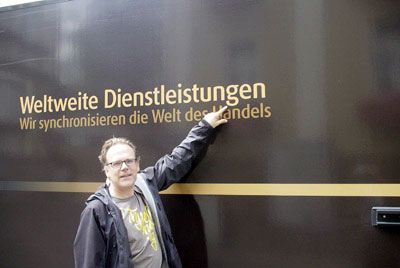
Lizenzstreit: FSI schließt VergleichAuf Typophile erschien in den frühen Morgenstunden eine
Pressmitteilung von FSI FontShop International zu einem länger
schwelenden Schriftlizenzstreit: Man habe sich mit einem nicht genannten
Corporate-Design-Unternehmen verglichen. Kommentatoren im Forum steuerten Ross
und Reiter bei: es geht um die Schrift FF Dax, von Future Brand
für das Redesign des Logistik-Konzerns UPS eingesetzt und nach
Auffassung von FSI nicht ordentlich lizenziert. Weiterlesen ...
Bei der beklagten Schrift handelt es sich um eine (so die Schriftexperten
bei Typophile) eigentümlich modifizierte FF Dax mit einem kleinen
g aus der FF Meta, ebenfalls eine Schrift aus FSIs
FontFont-Bibliothek. Dieser Zwiebelfisch war dem Fontblogger schon vor Monaten
aufgefallen:
![]() Zwiebelfisch: Der Kleinbuchstabe g passt nicht zur Grundschrift Die Übersetzung der Pressemitteilung: »FSI Fonts und Software GmbH (FontShop International) gibt heute bekannt, dass es einen Vergleich mit einem international anerkannten strategischen Markenentwicklungsunternehmen geschlossen hat, dessen Gegenstand eine Streitigkeit über Entwurf, Schöpfung und die Lizenzierung einer Schrift war – Bestandteil einer Arbeit für einen Kunden dieses Unternehmens. Das Unternehmen bestritt und verteidigte sich energisch gegen Vorwürfe, dass die besagte Schrift die Urheberrechte FSIs berühre oder dass die Schrift eine nicht-autorisierte Ableitung der von FSI herausgegebenen Schriften FF Dax und FF Meta sei. FSI erhob seine Vorwürfe im Februar 2005. Ohne jede Haftungszusage vereinbarten die Partner diese Angelegenheit gemäß den Bedingungen einer vertraulichen Vergleichsvereinbarung zu lösen, um die Unsicherheiten, Belastungen und Kosten eines möglichen langen Rechtsstreits zu vermeiden. Bestandteil des Vergleichs ist die Zusage des Unternehmens, 17.500 Dollar an FSI zu zahlen.« Die erste Kommentar zur Pressemitteilung auf Typophile: Yves Peters: »Glauben die Future-Brand-Leute wirklich, dass wir alle blind und doof sind?« Jared Benson: »Eine Lehre für Corporate Designer: Man kann nicht einfach an ein paar Buchstaben schrauben und das Ergebnis als seine eigene Schöpfung verkaufen.« Chris Keegan: »Futura Brand ist viieel zu billig davon gekommen. Ich bin sicher, dass sie UPS mehr als 17 K für deren ›eigene Schrift‹ abgeknöpft haben.« Herausgegeben: Mi - Januar 18, 2006 at 12:00 nachm. | |